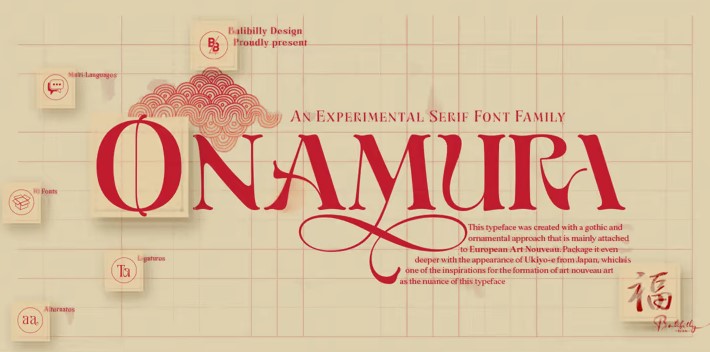
Изначально форма букв была вдохновлена готическим стилем романских декоративных букв в переходном искусстве Средневековья. Консервативный тип в готическую эпоху, особенно в декоративной романтике, привел к тому, что викторианский стиль был внедрен в несколько форм в качестве акцентов, связанных, но не вынужденных сочетаться. Закругленная засечка кажется условной в сочетании с исторически актуальной формой букв, создавая гармоничное сочетание. Стиль модерн также вдохновляет этот шрифт. Подход к архитектурному орнаменту с 1880 по 1915 год, перенявший динамичные линии и изгибы, характерные для цивилизации того времени. Продолжая путешествие во времени, мы также представляем более современную форму под влиянием оцифровки производных от модерна, которую принято называть психоделическим стилем.
Отдавая дань уважения предшественникам, мы представили шрифт The Onamura в японском стиле укиё-э, который повлиял на движение изобразительного искусства, сломавшее старое консервативное искусство в Европе.
Мы тщательно разработали этот шрифт, используя информацию о Средневековье, Укиё-э и Ар Нуво, которые оказали большое влияние на искусство во всем мире. В этом семействе шрифтов присутствуют вибрации сотрудничества. Оба они являются основой феноменального сочетания идеализма между западными и японскими художниками.
Состоящее из 10 шрифтов 10 весовых категорий, семейство имеет расширенный набор из более чем 850 глифов и поддерживает несколько языков, включая западноевропейский, центральноевропейский и юго-восточноевропейский. В нем реализованы такие передовые функции открытого шрифта, как стилистические альтернативы, произвольные лигатуры, ординаты, малые прописные буквы, дроби и формы, чувствительные к регистру.
Элегантные и утонченные детали этого шрифта вносят новый эстетический вклад, удовлетворяют современному стилю и дают возможность выбора для роскошных типографских проектов. Этот шрифт прекрасно подходит для заголовков с высокой степенью воздействия. Передовые возможности открытого шрифта потрясающе смотрятся на логотипах, брендинге, журналах, веб-сайтах и т.д.